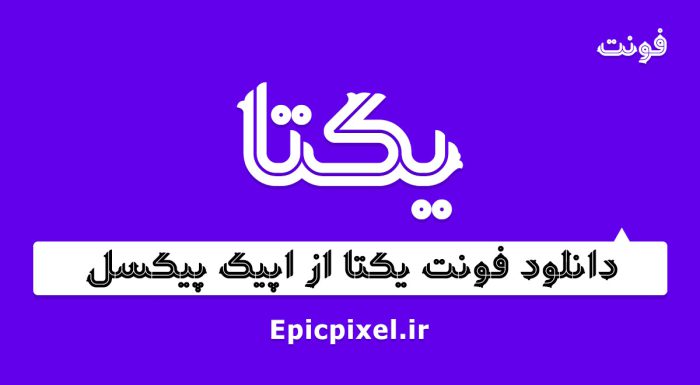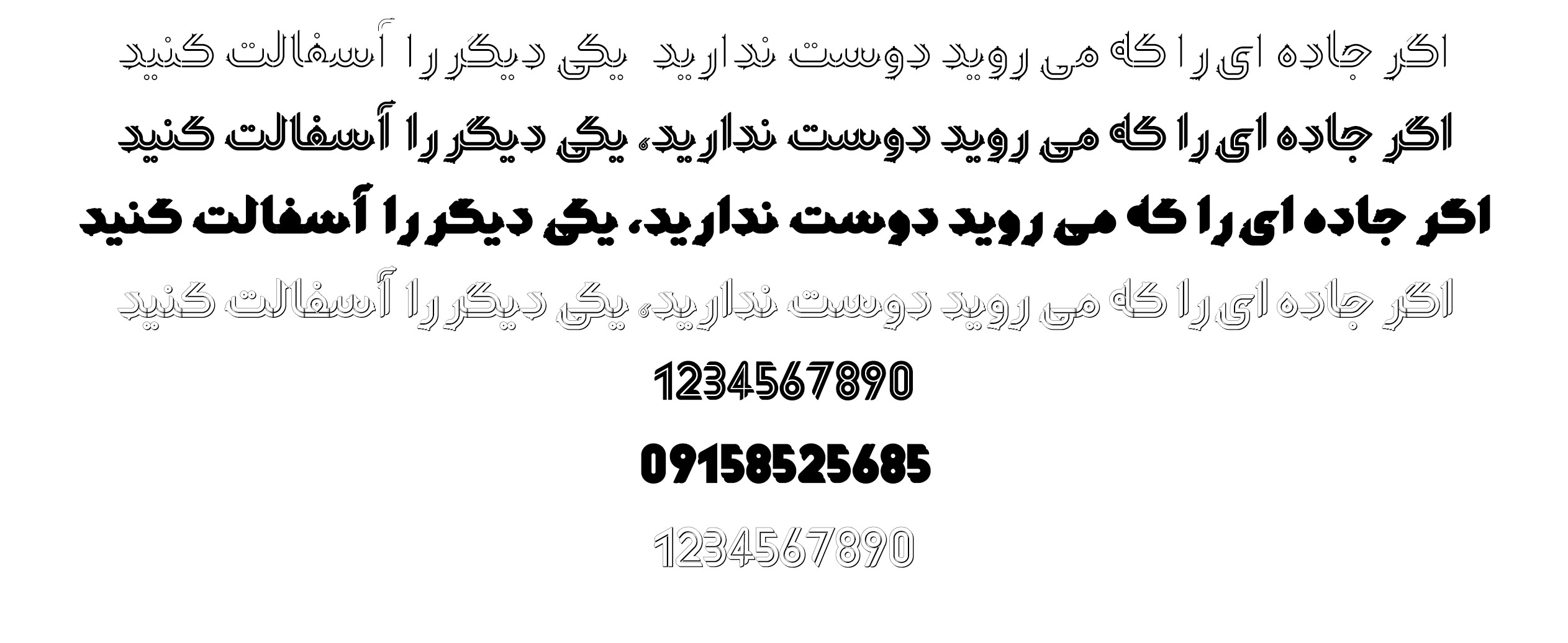
فونت یکتا، یک انتخاب هوشمندانه برای طراحانی است که به دنبال ترکیبی از اصالت و مدرنیته در آثار خود هستند. این فونت هندسی با ظرافت خاصی طراحی شده و با داشتن تزئینات ظریف و الهام گرفته از نقوش اسلیمی، حس و حالی ایرانی و فرهنگی به نوشته ها می بخشد. در واقع، یکتا با وجود ساختار هندسی اش، برای موضوعات مذهبی، ادبی و هنری بسیار مناسب است و برخلاف فونت های هندسی دیگر، محدودیتی در این زمینه ها ندارد.
یکی از ویژگی های برجسته فونت یکتا، خوانایی بالای آن در اندازه های مختلف است که آن را برای استفاده در عناوین، متون کوتاه و حتی لوگوها ایده آل می سازد. این فونت با ایجاد تعادل بین فرم های مدرن و تزئینات سنتی، به نوشته های شما هویتی منحصربه فرد می بخشد و در عین حال، سادگی و زیبایی را به طور همزمان ارائه می دهد. اگر به دنبال فونتی هستید که هم در طراحی های چاپی و هم در محیط دیجیتال بدرخشد و جلوه ای خاص به کارتان ببخشد، فونت یکتا گزینه ای بی نظیر است. این فونت با ارائه سبکی متفاوت، به شما کمک می کند تا آثاری چشم نواز و ماندگار خلق کنید.